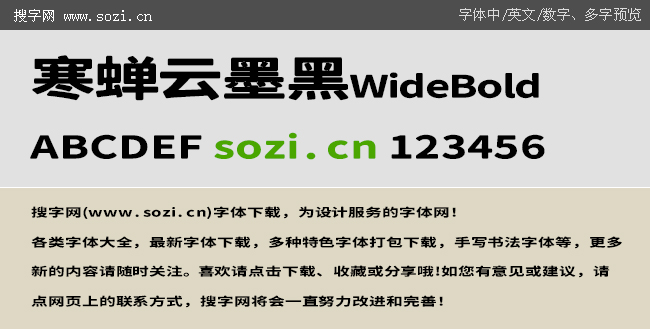
寒蟬云墨黑WideBold
搜字網(wǎng)給大家提供一款寒蟬云墨黑WideBold中文字體下載,寒蟬云墨黑是基于思源黑體進行修改調(diào)整的一款黑體字體,字體添加了圓角,效果看上去更加溫潤。排版細節(jié)也進行了優(yōu)化,并重構(gòu)了字重比例。適用于標(biāo)題設(shè)計、海報設(shè)計、書籍排版以及網(wǎng)頁設(shè)計等應(yīng)用。